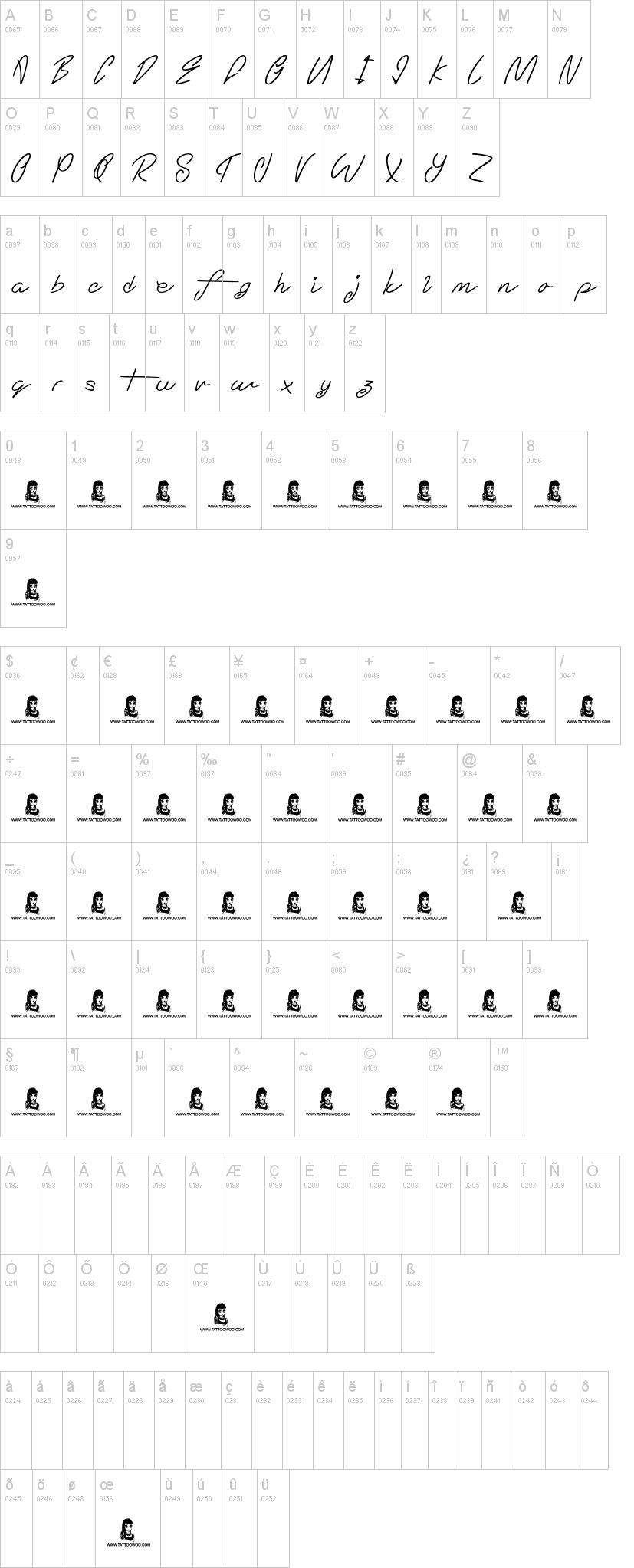
Eternal Fascination
Eternal Fascination 是一款经典的古典风格字体,由著名设计师Gerald Gallo设计。它有一种古典的风格,细节丰富,灵动而优雅。它的字形有着温暖的气息,让人感受到一种深远的传统,使它成为一款独特的、有趣的字体。它适合用于各种类型的印刷品,如书籍、杂志、海报、广告等,可以让您的设计更加出色。
Eternal Fascination是一款非常不错的手写艺术字体,具有很好的视觉感,适合于文化类的宣传设计、商业类品牌的广告和产品包装设计以及个性化文字排版等较多场景。